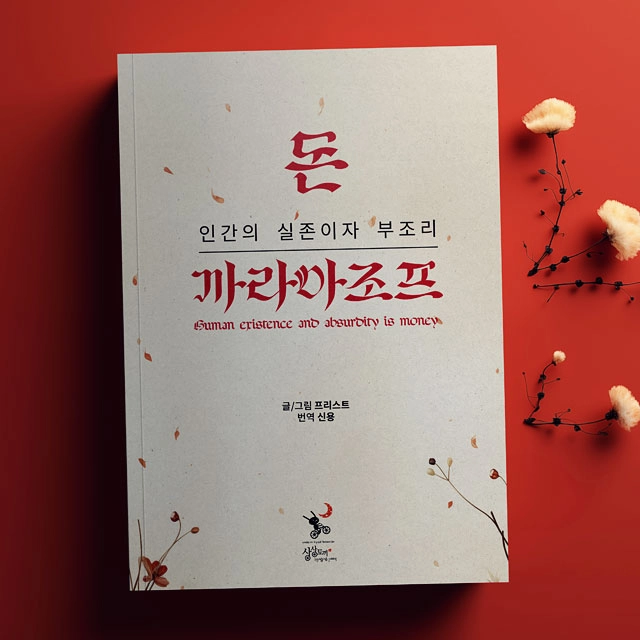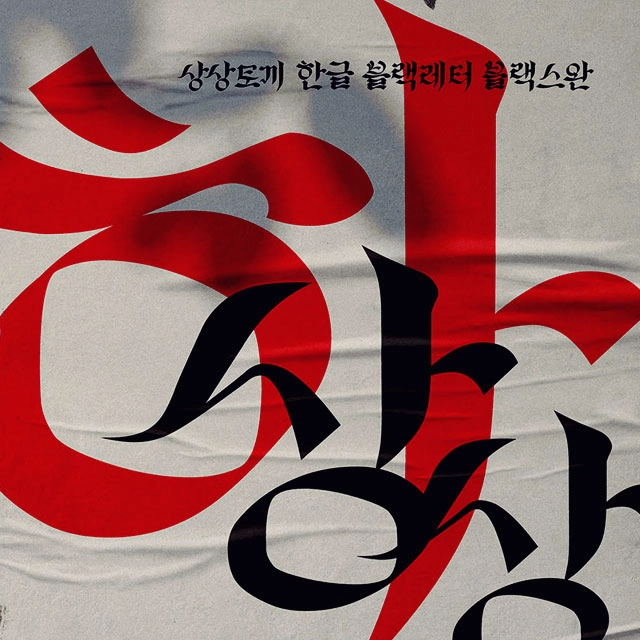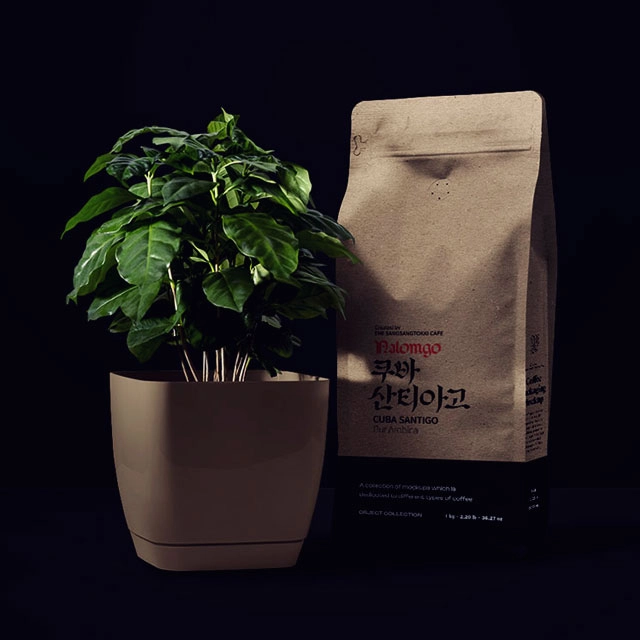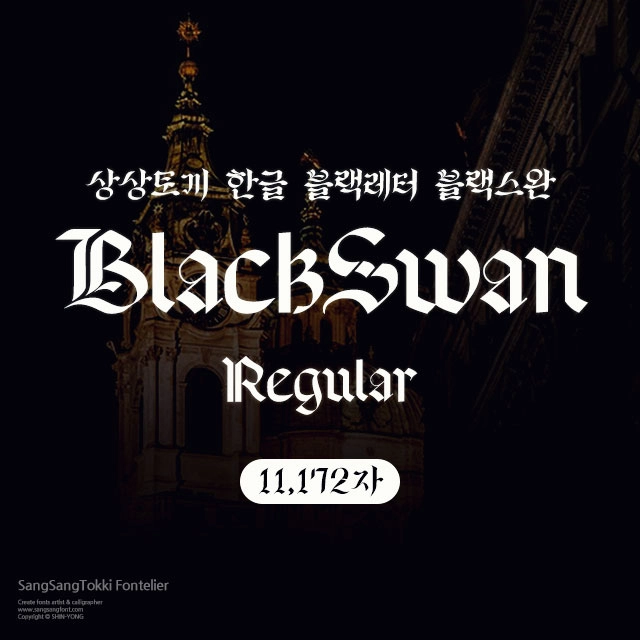
블랙스완 레귤러
상상토끼의 한글 블랙레터 시리즈 두번째 폰트, 블랙스완 레귤러
| 블랙레터라 함은 획이 두껍고 글자의 폭이 좁아서 이름 그대로 지면이 검게 보이는 글자체를 의미합니다. 서양 문화 최초의 금속활자 인쇄본으로 알려진 구텐베르크 성경에 활자로 사용된 서체입니다. |
| 획이 가로에서 세로로 바뀔때 부드럽게 곡선으로 굴려지지 않고 딱딱하게 꺾어서 쓰기 때문에 '꺾어 쓰는 글자체'라고 부르기도 합니다. |
| 블랙레터의 형태는 시간과 장소가 바뀌면서 변화하게 됩니다. 꺾어 쓰는 글자로 딱딱한 이미지를 가졌던 텍스투라는 이탈리아로 건너가서 폭이 넓고 둥근 로툰다로 변화했습니다. 그후 독일에서는 르네상스 시대에 슈바바허, 바로크 시대에 프락투어로 진화해 20세기로 이어졌습니다. |
| 블래레터는 20세기 중반까지도 독일에서 널리 쓰였는데요, 그중 프락투어는 2차대전 당시 히틀러가 나찌 프로파간다에 주로 사용했던 글자체이기도 합니다. 그때문에 당시에는 블래레터에 부정적인 인식이 생기기도 했습니다. |
| 블랙레터의 여러 형태 중에서 폭이 넓은 둥근 획과 완만한 꺾임을 핵심 요소로 가지고 있는 로툰다를 상상토끼의 두번째 한글 블랙레터로 선보입니다. 한글 디자인에는 우리 전통 붓글씨 획의 특성을 살짝 가미하여 가독성을 심각하게 해치지 않는 심플한 서체로 마무리하였습니다. |
| 블랙레터라 함은 획이 두껍고 글자의 폭이 좁아서 이름 그대로 지면이 검게 보이는 글자체를 의미합니다. 서양 문화 최초의 금속활자 인쇄본으로 알려진 구텐베르크 성경에 활자로 사용된 서체입니다. |
| 획이 가로에서 세로로 바뀔때 부드럽게 곡선으로 굴려지지 않고 딱딱하게 꺾어서 쓰기 때문에 '꺾어 쓰는 글자체'라고 부르기도 합니다. |
| 블랙레터의 형태는 시간과 장소가 바뀌면서 변화하게 됩니다. 꺾어 쓰는 글자로 딱딱한 이미지를 가졌던 텍스투라는 이탈리아로 건너가서 폭이 넓고 둥근 로툰다로 변화했습니다. 그후 독일에서는 르네상스 시대에 슈바바허, 바로크 시대에 프락투어로 진화해 20세기로 이어졌습니다. |
| 블래레터는 20세기 중반까지도 독일에서 널리 쓰였는데요, 그중 프락투어는 2차대전 당시 히틀러가 나찌 프로파간다에 주로 사용했던 글자체이기도 합니다. 그때문에 당시에는 블래레터에 부정적인 인식이 생기기도 했습니다. |
| 블랙레터의 여러 형태 중에서 폭이 넓은 둥근 획과 완만한 꺾임을 핵심 요소로 가지고 있는 로툰다를 상상토끼의 두번째 한글 블랙레터로 선보입니다. 한글 디자인에는 우리 전통 붓글씨 획의 특성을 살짝 가미하여 가독성을 심각하게 해치지 않는 심플한 서체로 마무리하였습니다. |